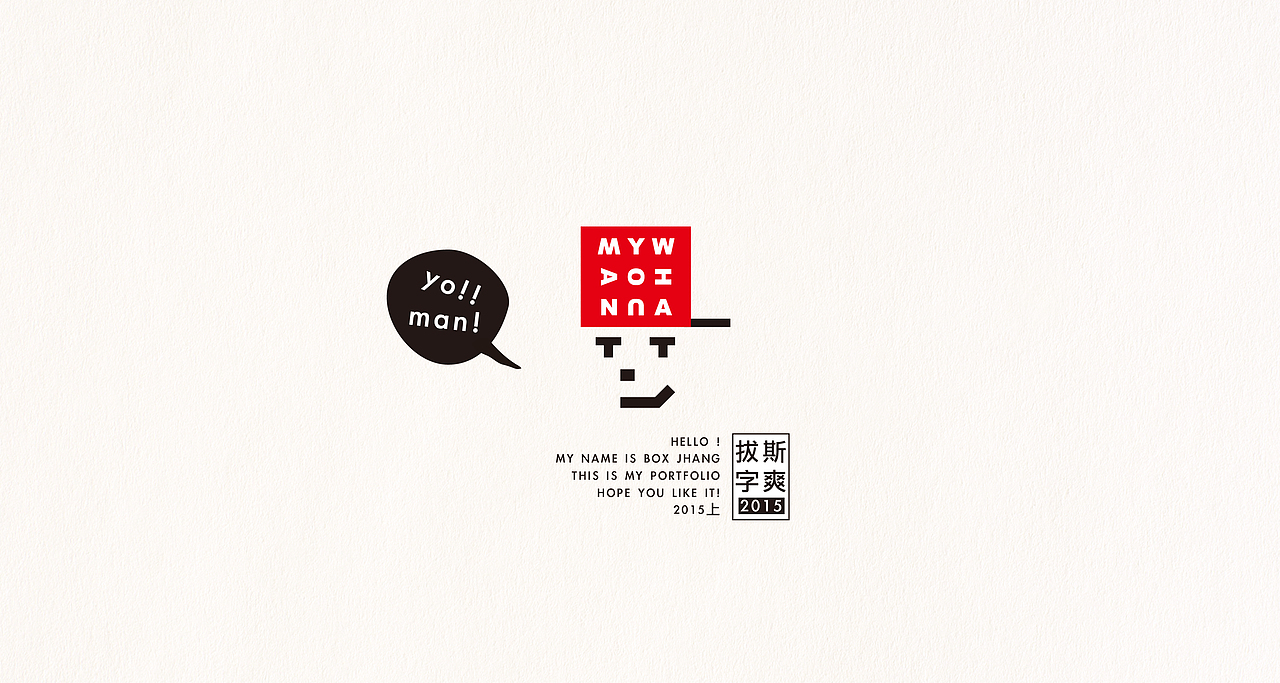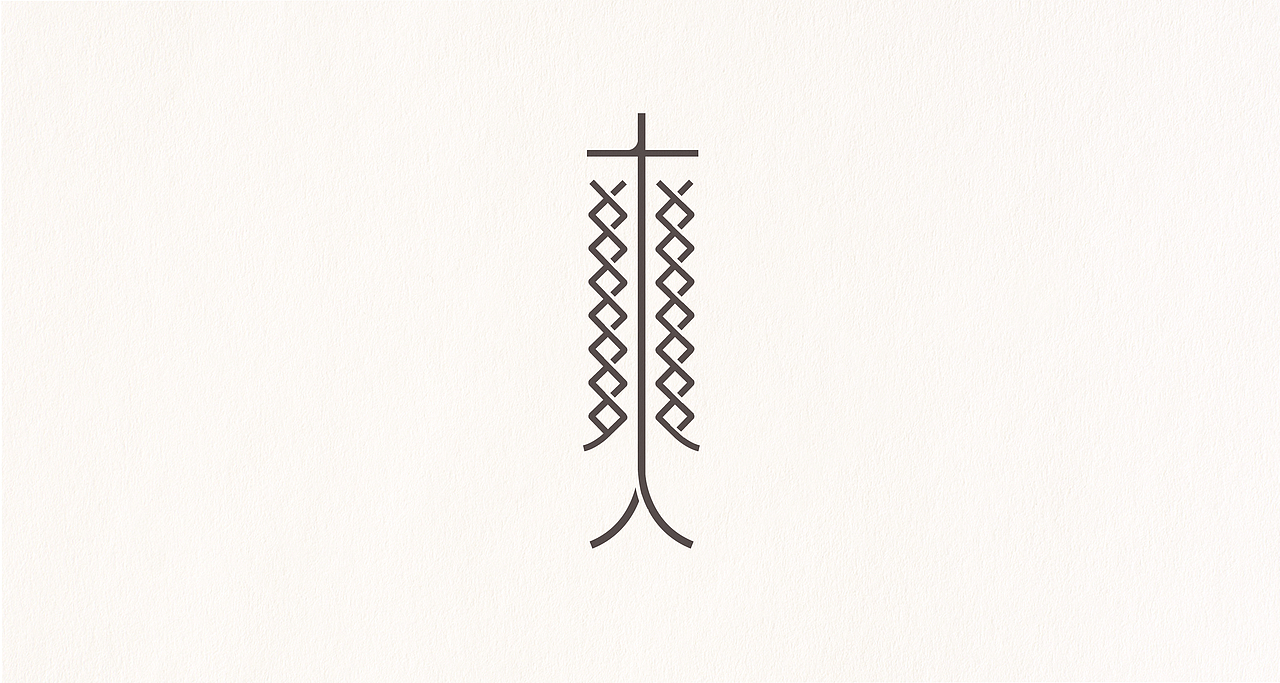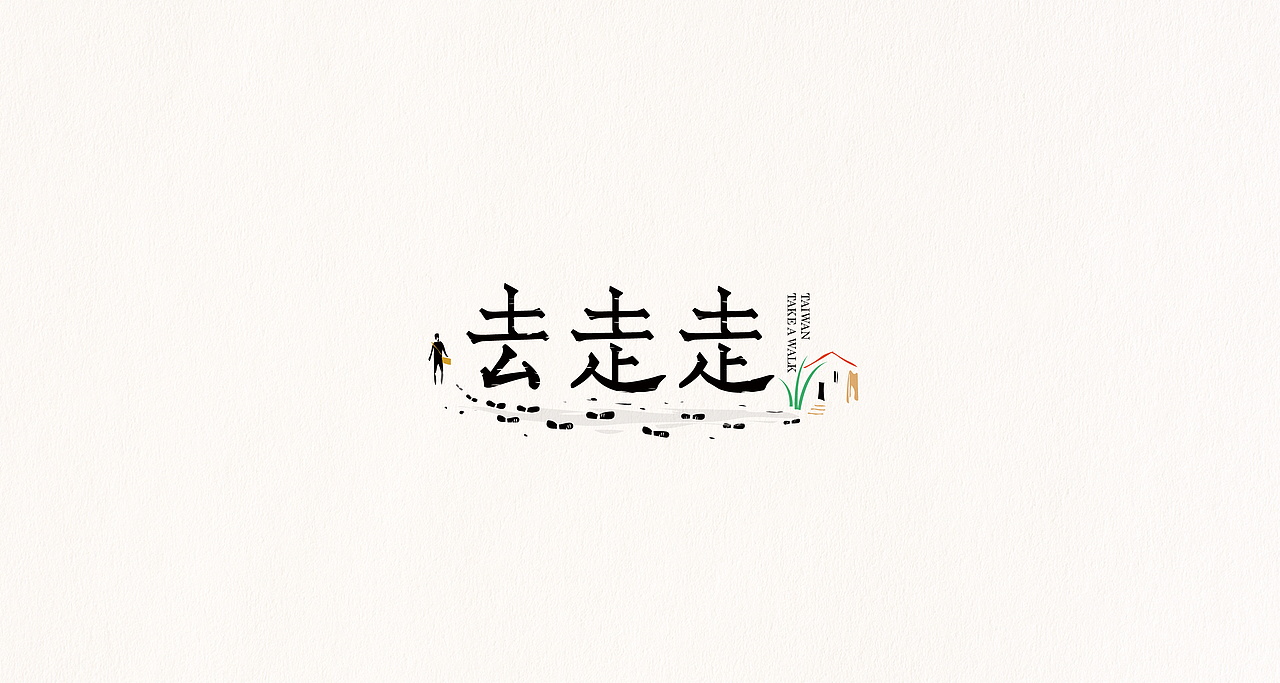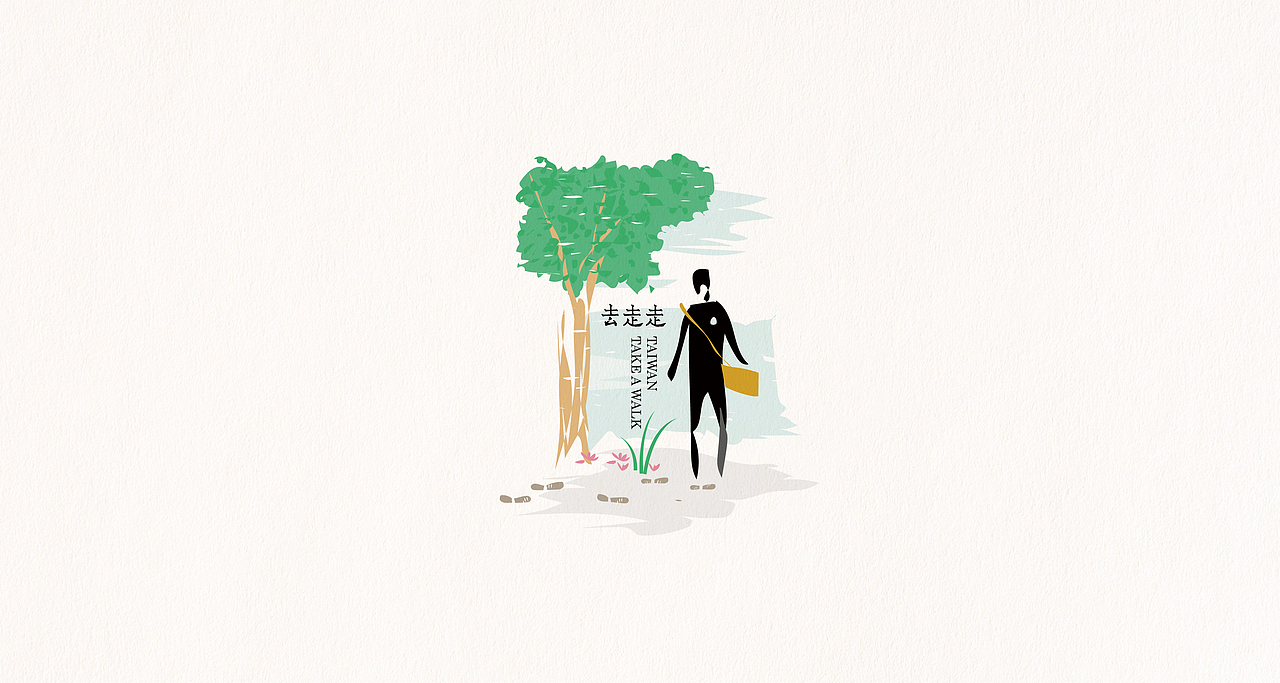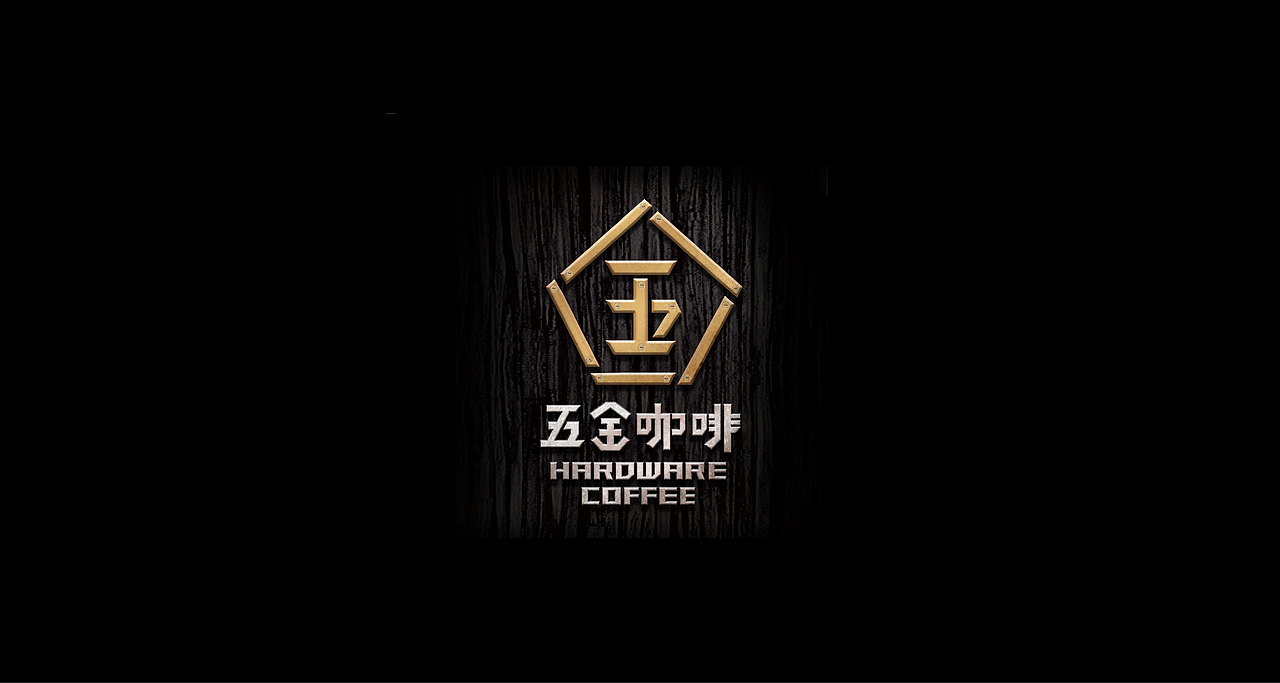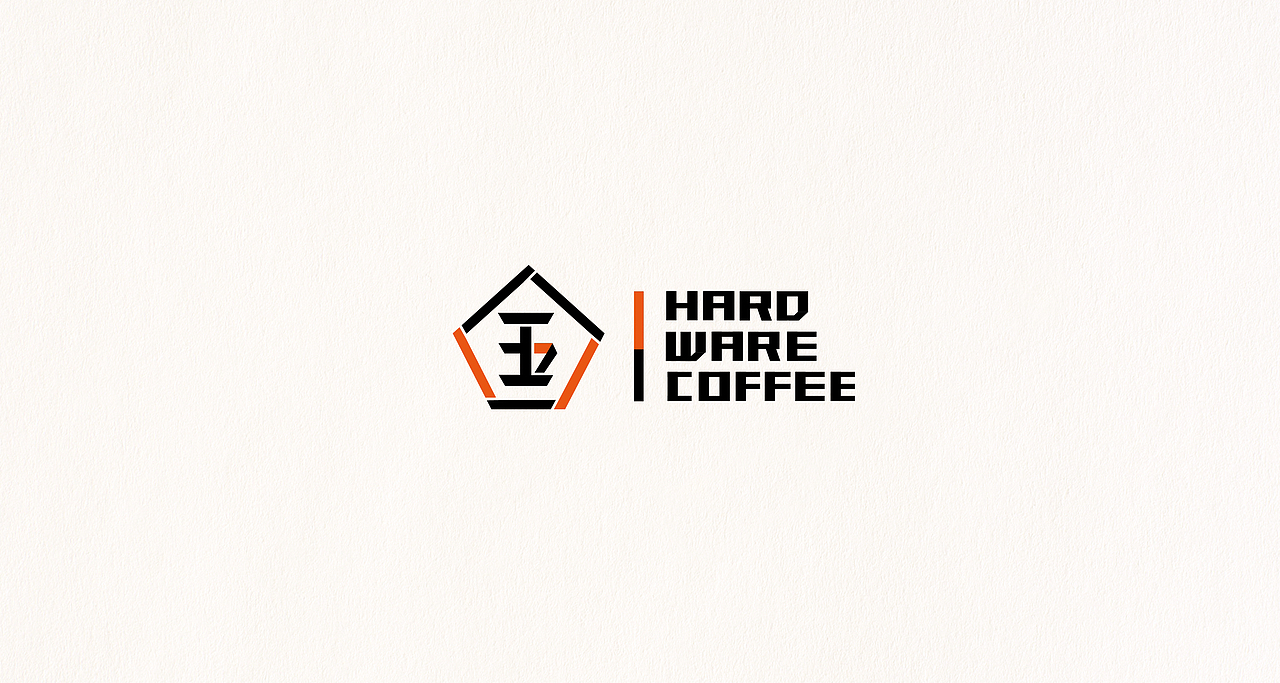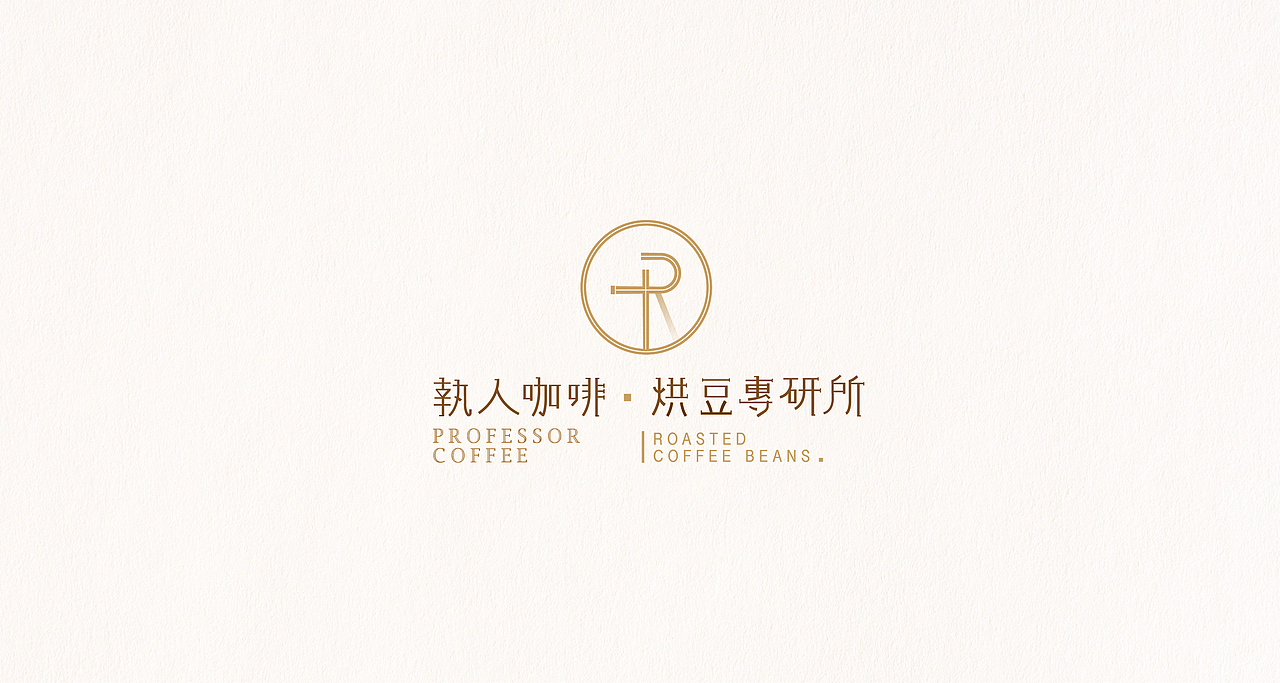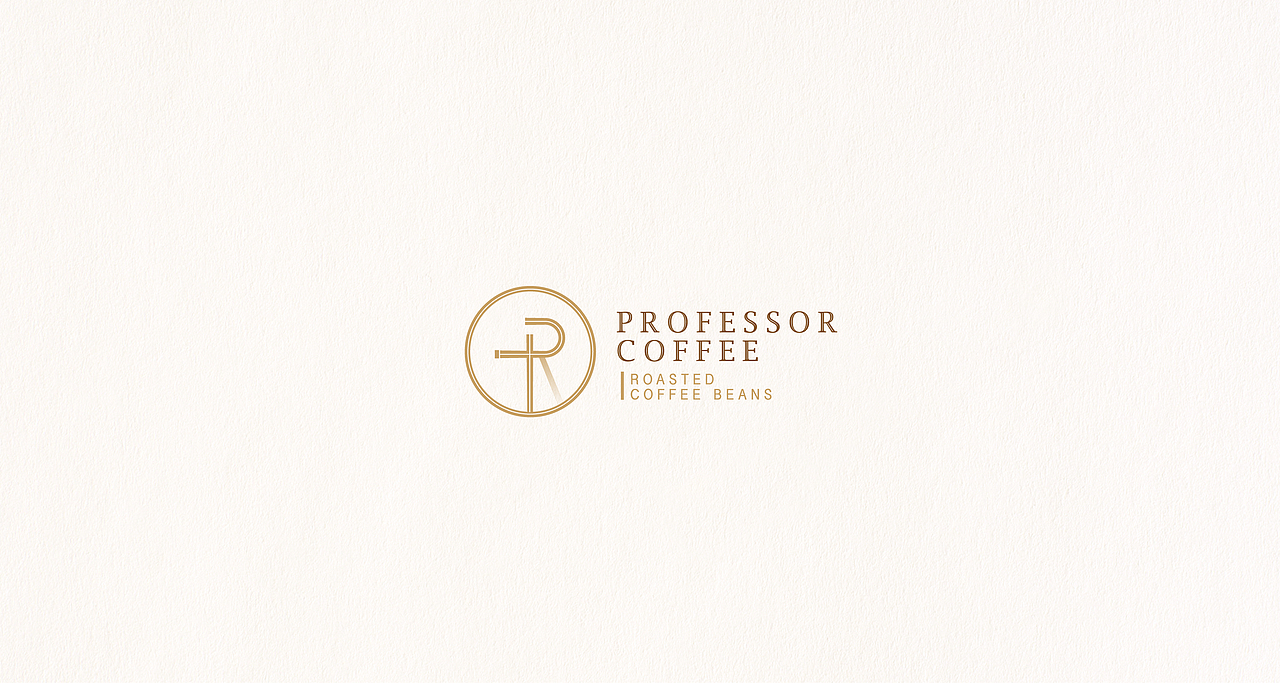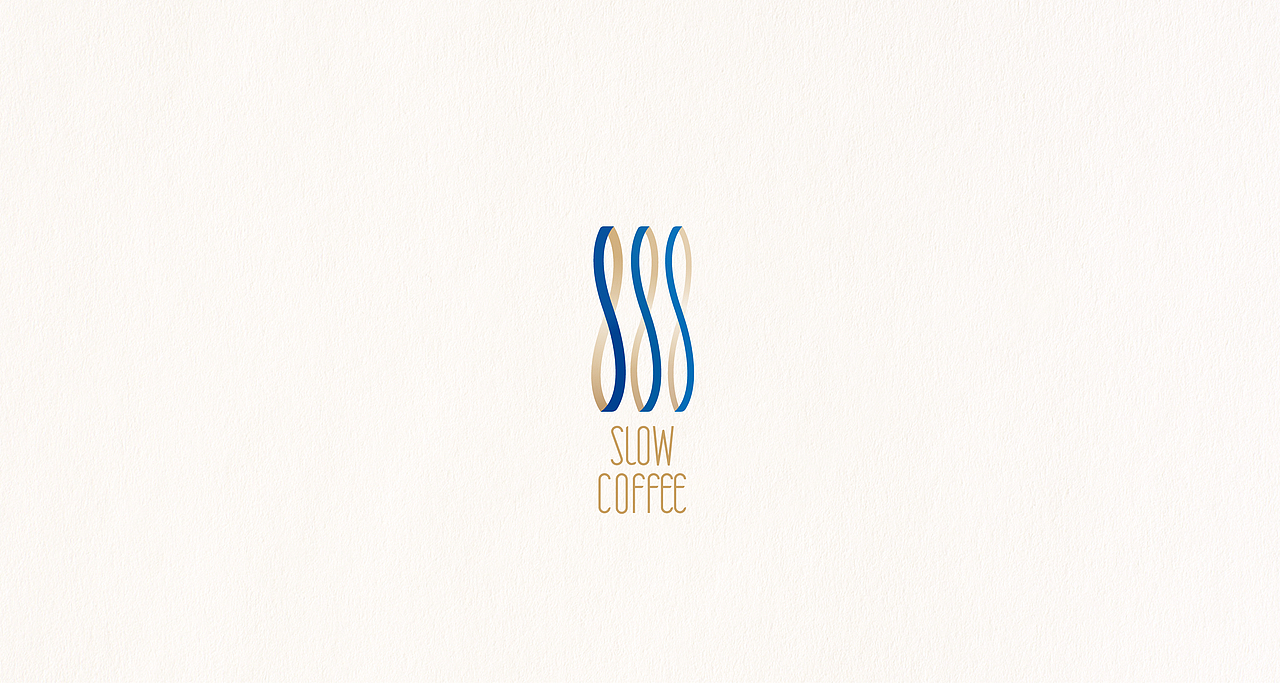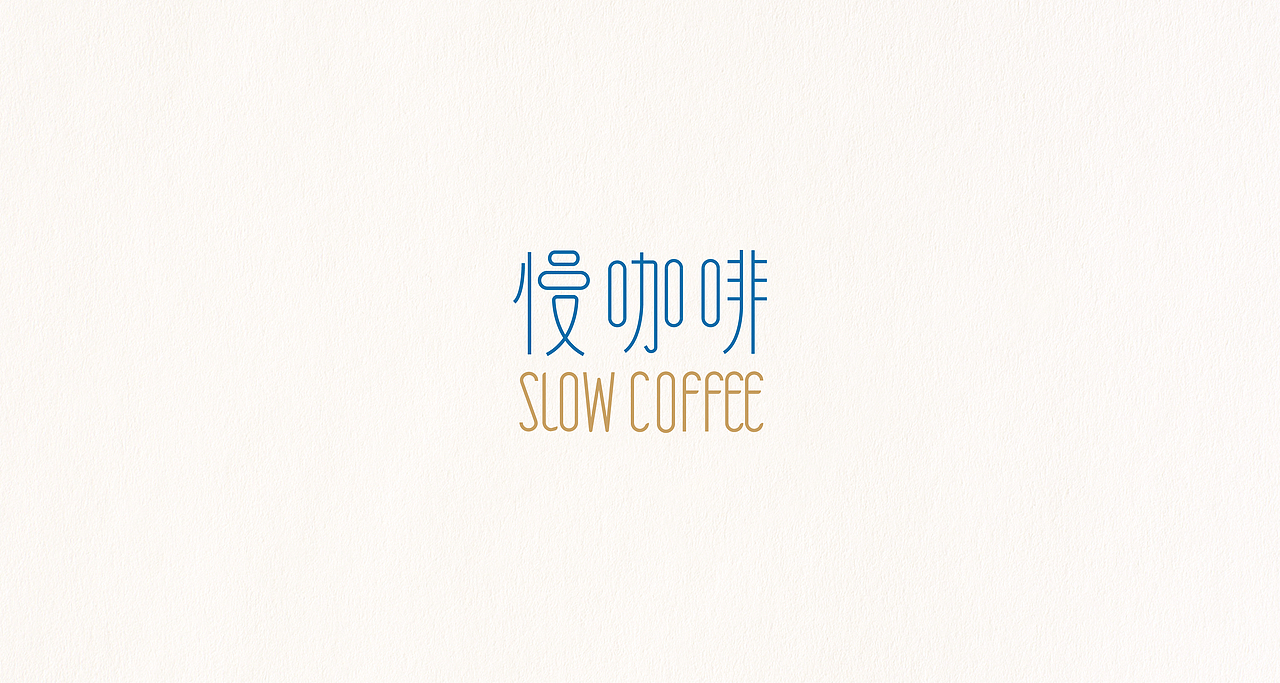
2015上半季,拔斯字爽作品集
哈囉:)跟各位爺兒們&姊姊們,或是文青小鮮肉們交流交流囉,
小弟我最近想到這強大的論壇,於是乎又跑過來獻醜了。
我一整個超愛畫圖,得了那種『不畫手會癢,成天在字爽』
希望有機會能接到更有趣的案子,弟我很厚工,
『只要你願意,我們誠相許』
PS
我沒有特定的風格,就愛玩,但現在的作品比較簡易,
正在累計大型作品的能量,
好好玩吧,設計沒有絕對,把心敞開玩得開心,作品就會跟著熱起來,一種相由心生的道理。
最後~我叫拔斯先生,yo! man! nice to meet you;P
一種爽到翻掉的概念XD
來去走走吧,放寬心
找屬於自己心中的風景
五金咖啡,標誌設計(今年第一家店)(也是全台灣唯一五金咖啡)
五金咖啡英文標準字組合
執人咖啡烘豆專研所(今年第二家店)
慢咖啡(今年第三家店)
慢咖啡中英標準字
下徑口咖啡(今年第四家店籌備中)
台灣插畫家品牌(剛起步籌備中)
我插畫作品用的XD
交通大學傳科所下半學年活動標準字
IMP光義包裝工業,標誌提案
IMP標準字設計
交通大學校園御守標準字設計
我們都需要希望
伺服器無法正常運作
我是設計的粗人
嘿嘿~開動:P
因為壞,所以打叉叉
用Design 組成的『設計』
撕裂了,用力補
BOOM!!!!!
解密吧:)
鬥,摩擦&傳承
yo~
我英文名字叫做KEN,哈哈哈哈
狠狠愛!
我的新版名片,哈哈哈,很少看到畫那麼多的card吧?